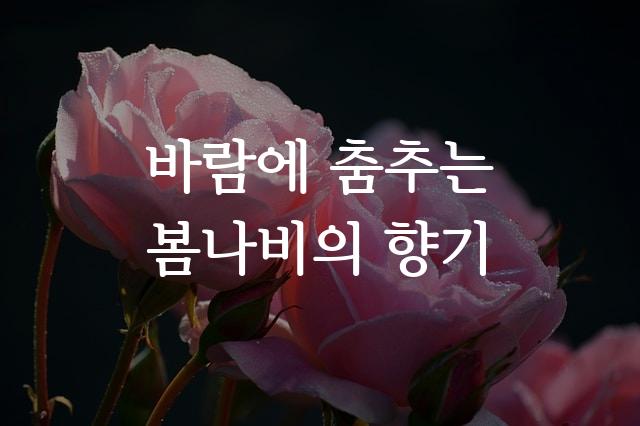
김남윤체
김남윤체는 윤디자인에서 제작한 어른 손글씨 스타일의 폰트로, 또박또박한 필기체가 안정감과 신뢰감을 줍니다. 이 폰트는 디지털 문서에서도 글자의 개성과 감성을 살려줍니다.
감성을 담은 필체, 디지털 세상의 인간적인 손길 400
이 폰트는 한국어, 영어, 일본어, 특수문자 를 지원하며 실제 다국어 콘텐츠에 활용했을 때의 느낌을 생생하게 확인할 수 있습니다.
이 폰트의 인사이트!
친근하고 따뜻한 목소리로, 마치 오랜 지인과 대화를 나누는 듯한 인상을 줍니다.
김남윤체은(는) 손글씨, 감성적인, 부드러움 계열의 생김새를 가지고 있으며
출판 디자인, 제품 포장, 출판물 제목 등에서 자주 활용되며, 효과적인 메시지 전달에 적합합니다.
이 폰트는 출판/미디어, 크리에이티브, 문화/예술 분야에 잘 어울리며,
감성적인, 전통적, 세련된 느낌을 담고 있는 것이 특징입니다.